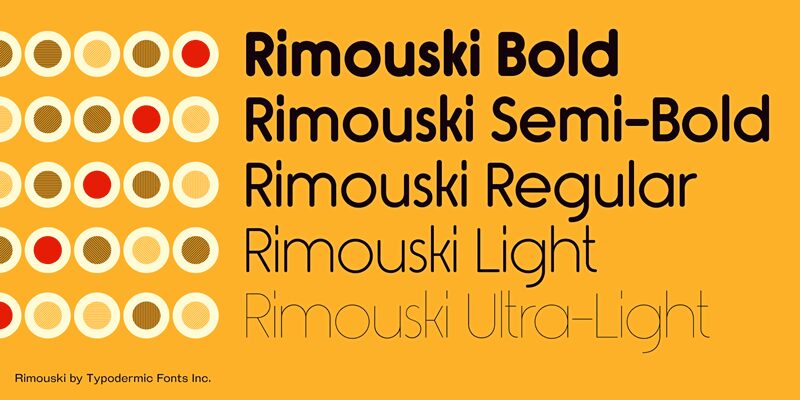
Rimouski ist eine geometrische Schriftfamilie mit abgerundeten Formen. Nutzen Sie die OpenType-Funktion "stylistic alternates", um eine Vielzahl von ungewöhnlich geneigten Zeichen zu aktivieren.